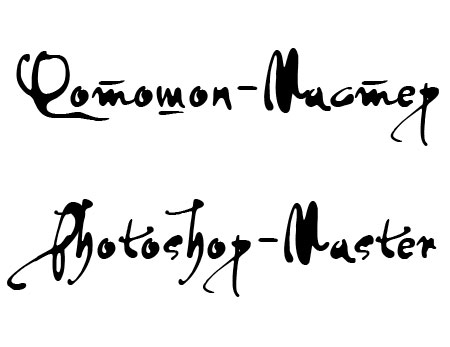
бомбовый шрифт.
красивый фрифт *^*
а врачебный почерк похож :) но беру
Ангел с неба это не водянистый,а скорее чернильный шрифт :)
Ух ты ж!Прикольный.Хоть и неразборчивый.
Прикольно но качать небуду нелюблю каракули.